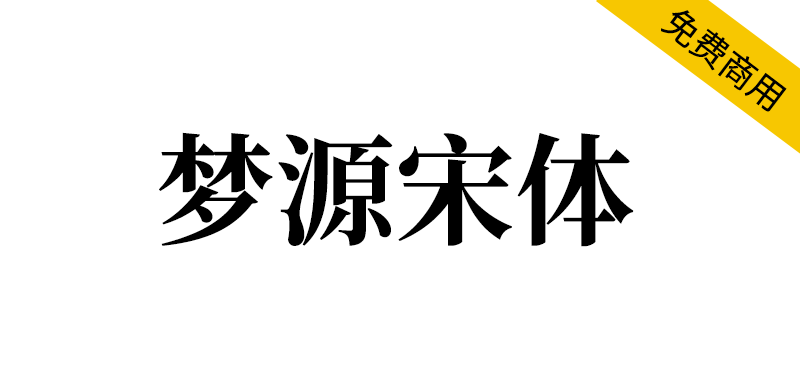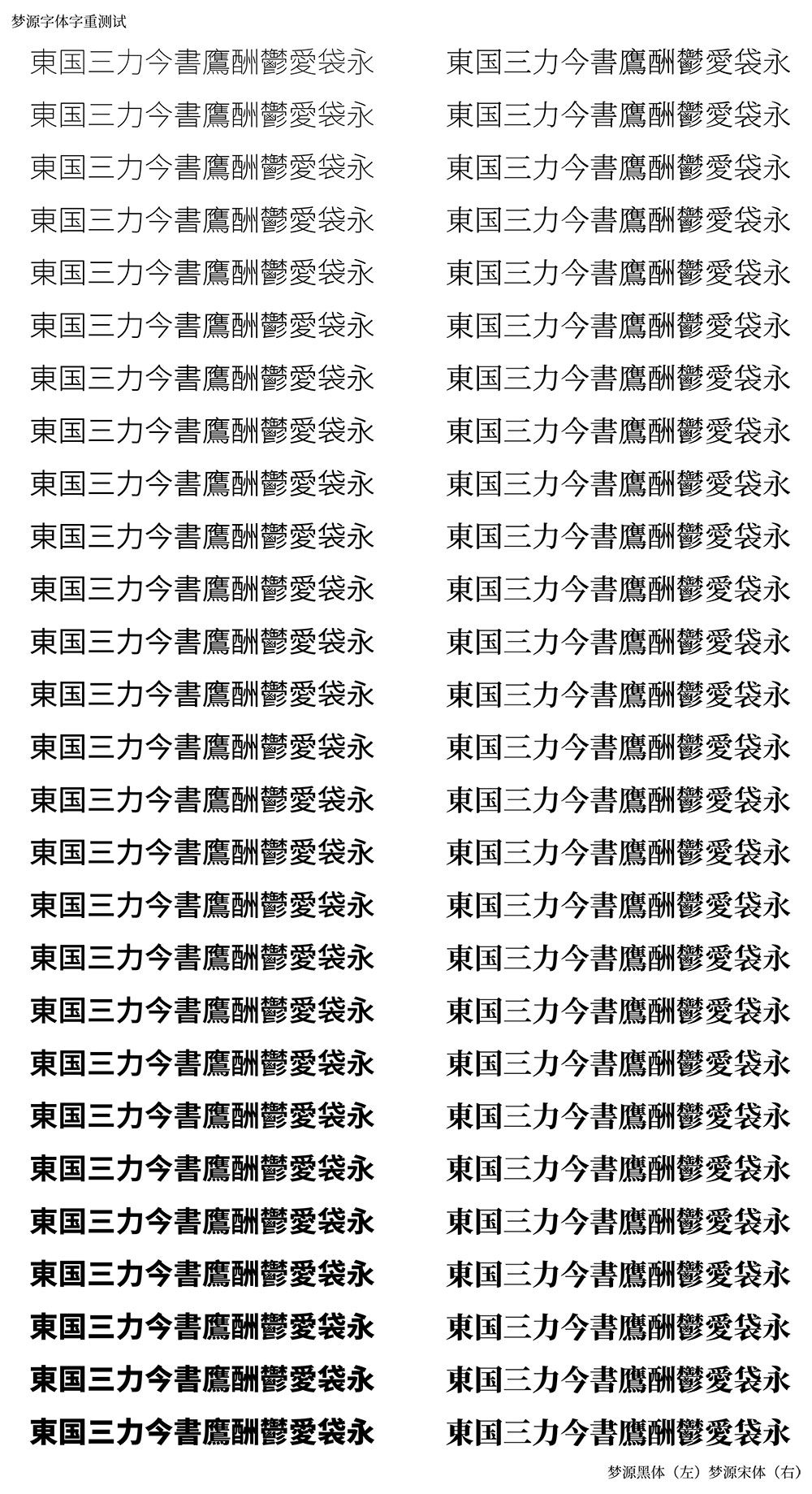
梦源宋体源自思源宋体多语言字体家族,兼顾字重、功能与兼容性,货真价实的27字重!做设计起飞的赶脚!免费商用!绝非什么小作坊的描边加粗!
可变版思源字体使精细的字重调节成为了可能。然而,可变字体因轮廓重叠、渲染故障、软件兼容性等原因给实际使用造成了阻碍。本项目将可变版思源字体的大量中间字重实例化为传统单字重字体,合并了重叠的曲线轮廓,在保证最大兼容性的前提下,提供更加细腻、丰富的字重选择。此外,本项目修复了思源系列广泛存在的 Adobe 行高过大问题。本系列字体的其他功能(如字形、竖排、kerning、多语言、异体字、曲线精度等)与思源系列保持完全一致,未做任何修改。
技术规格
样式:W1 - W27 共计 27 字重
字符集:完整版含 6,5535 字符
异体字支持:简、台繁、港繁、日、韩
OpenType 功能(竖排支持等):完整收录,与思源系列相同
Adobe 行高:标准行高,已修复思源系列存在的行高过大问题
Microsoft Office Style-Link:加粗按钮 B 链接黑体的 W12 与 W22 字重,以及宋体的 W7 与 W20 字重
曲线格式:二次贝塞尔曲线
曲线精度(UPM, units per em):2048,即原版 OpenType/CFF 三次曲线的无损转换
屏显渲染策略:全字号亚像素抗锯齿(Windows 10 及更新版本)
字重:本项目以可变版思源黑体和思源宋体为母版,对其字重轴 wght 进行插值运算,提取中间字重。插值算法经过了如下考量:
1、暴露给最终用户的 wght 轴经 Adobe 添加的 avar 表人工干预,导致字重随 wght 非线性增大(参见 issue #6)。插值算法需排除 avar 表的干扰;
2、加粗时,黑体和宋体的黑度变化不同:黑体的横竖笔画同时变粗,而宋体只有竖笔画变粗,因此在人眼看来,黑体的加粗速度要高于宋体,且其细体字重比粗体对粗度的变化更为敏感。简单的线性插值适用于宋体,但如果直接用在黑体上,就会导致细体字重被粗体“挤压”。
插值算法:
1、绕开思源可变源文件中的 avar 表,确保插值算法不受人工预设值干扰;
2、梦源宋体采用线性插值(linear interpolation):从最细端 250 开始,粗度每步增加常数 25 ,直到最粗端 900,得到 250-275-300-...900 共计 27 字重;
3、梦源黑体采用二次多项式插值(quadratic interpolation):从最细端 250 开始,粗度每步增加 19.4 + f ^ 2;其中,系数 f 的起始值为 1,每一步增大 0.1;以此类推,直到最粗端 900,得到 250-270.4-291.01-...-900 共计 27 字重。
因为插值算法绕过了思源可变内置的 avar 表,所以本项目采用的 wght 值与思源可变字体没有任何关联,也没有与思源在数值上完美对应的字重。在实际使用中,可对比思源字体找出梦源字体最接近的字重。